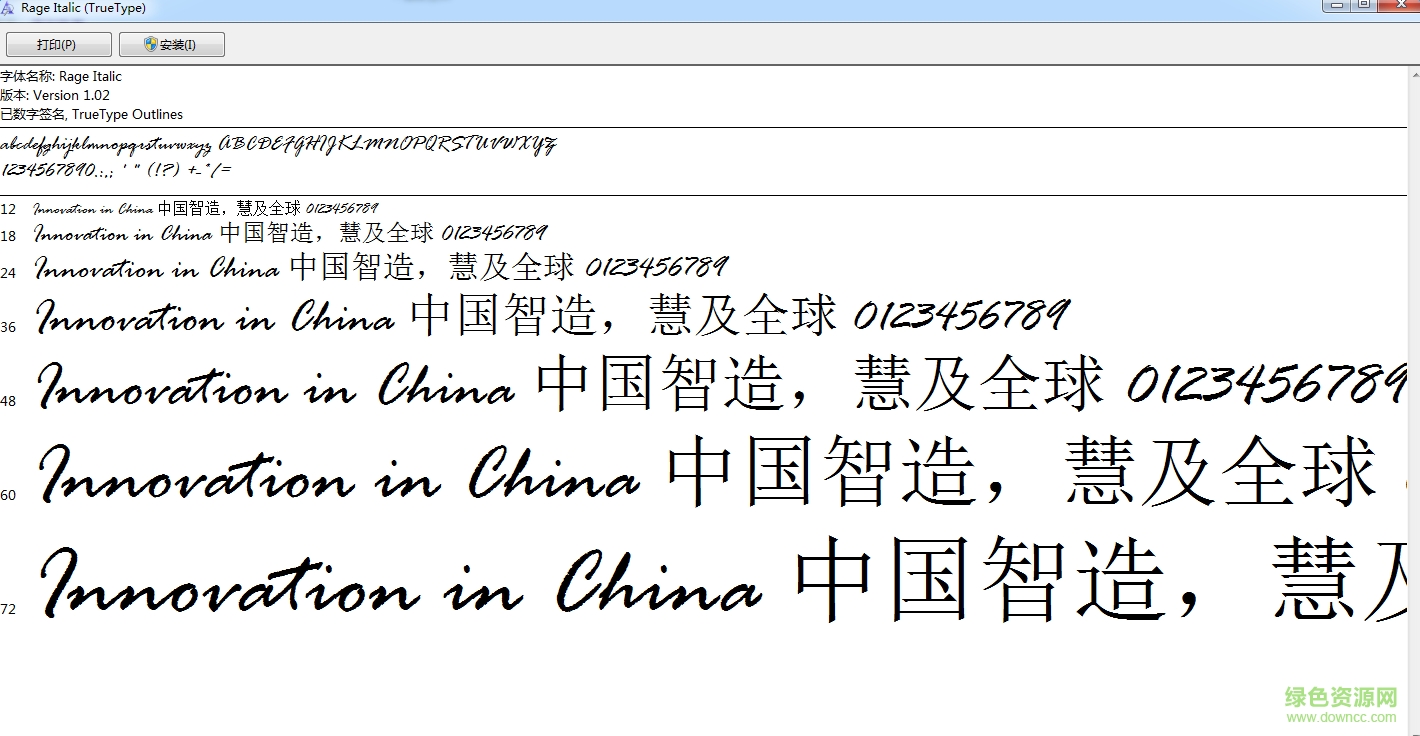
rageitalic字體
rage italic字體是一款十分漂亮的英文斜體字體,線條夸張,字形花哨,可應(yīng)用于涂鴉設(shè)計、美術(shù)設(shè)計、創(chuàng)意海報、飾品包裝等眾多領(lǐng)域,歡迎大家在綠色資源網(wǎng)下載!
斜體字體介紹
斜體是在正常字體樣式基礎(chǔ)上,通過傾斜字體實現(xiàn)的一種字體樣式。 中文(漢字)的斜體實際上都是單純將字面從正方形改為平行四邊形的“偽斜體”。
傳統(tǒng)排版中,漢字一般不使用斜體。電腦的普及給字體變形帶來了極大方便,才將西文這一習(xí)慣延伸到中文中。